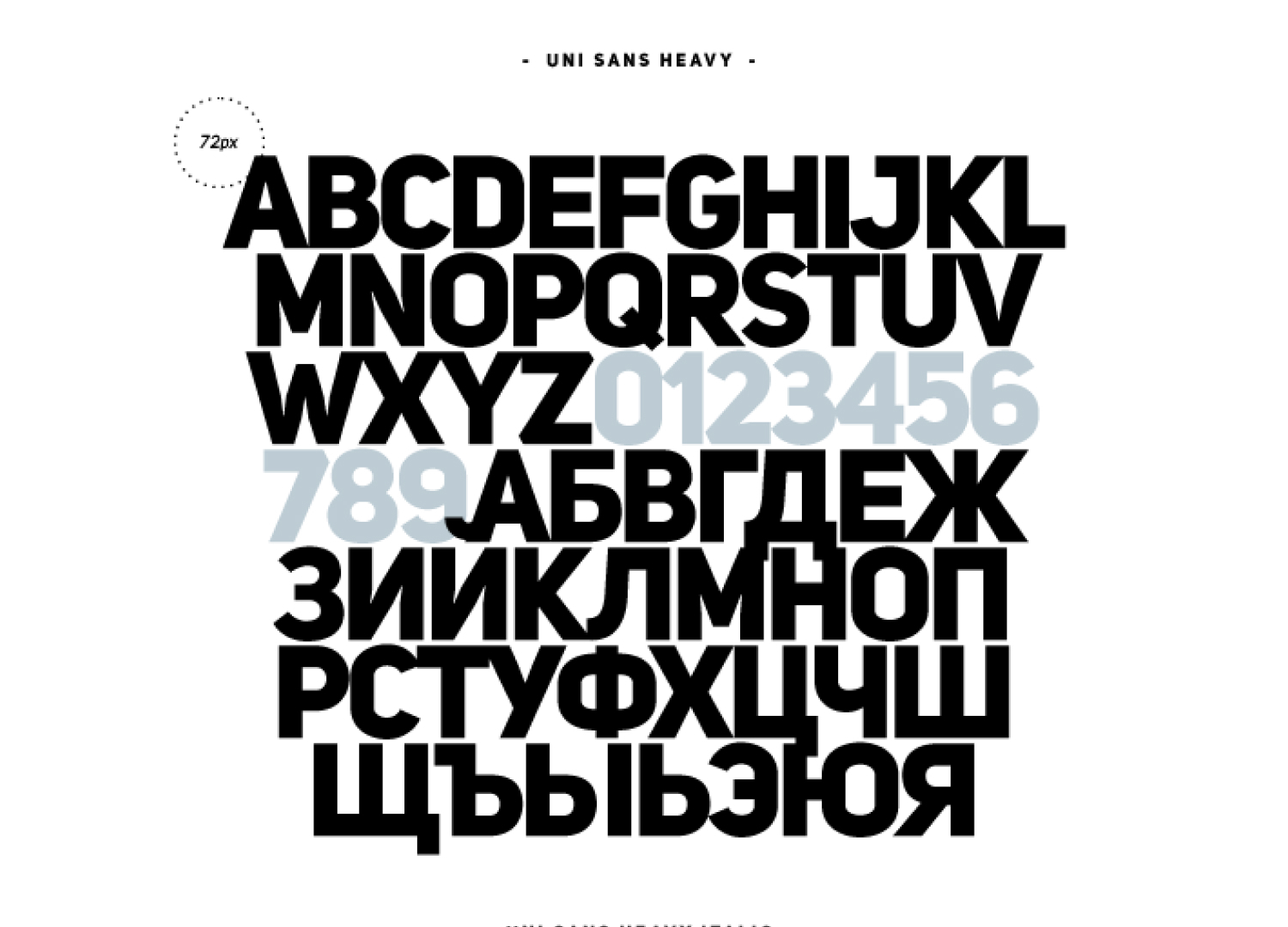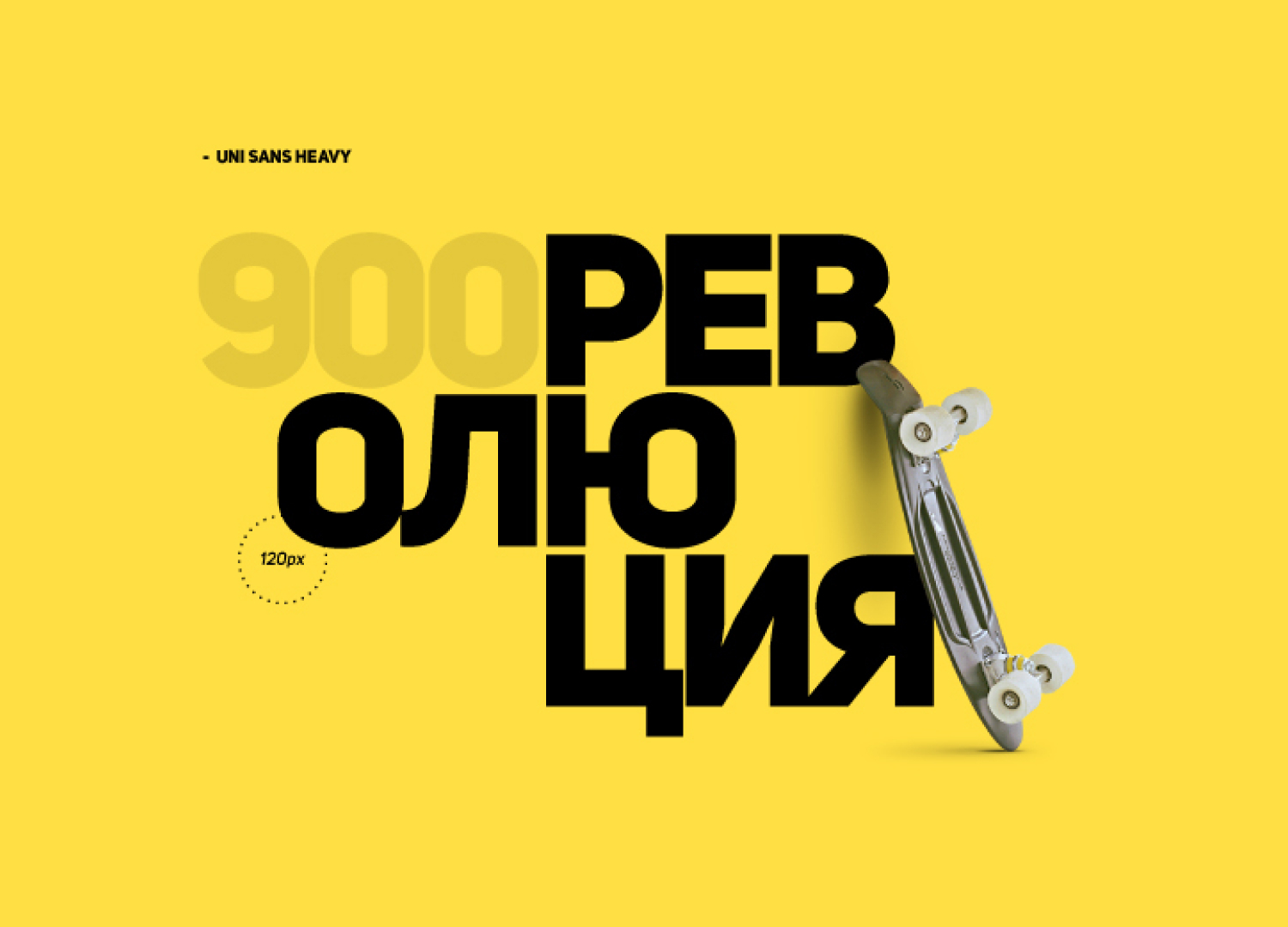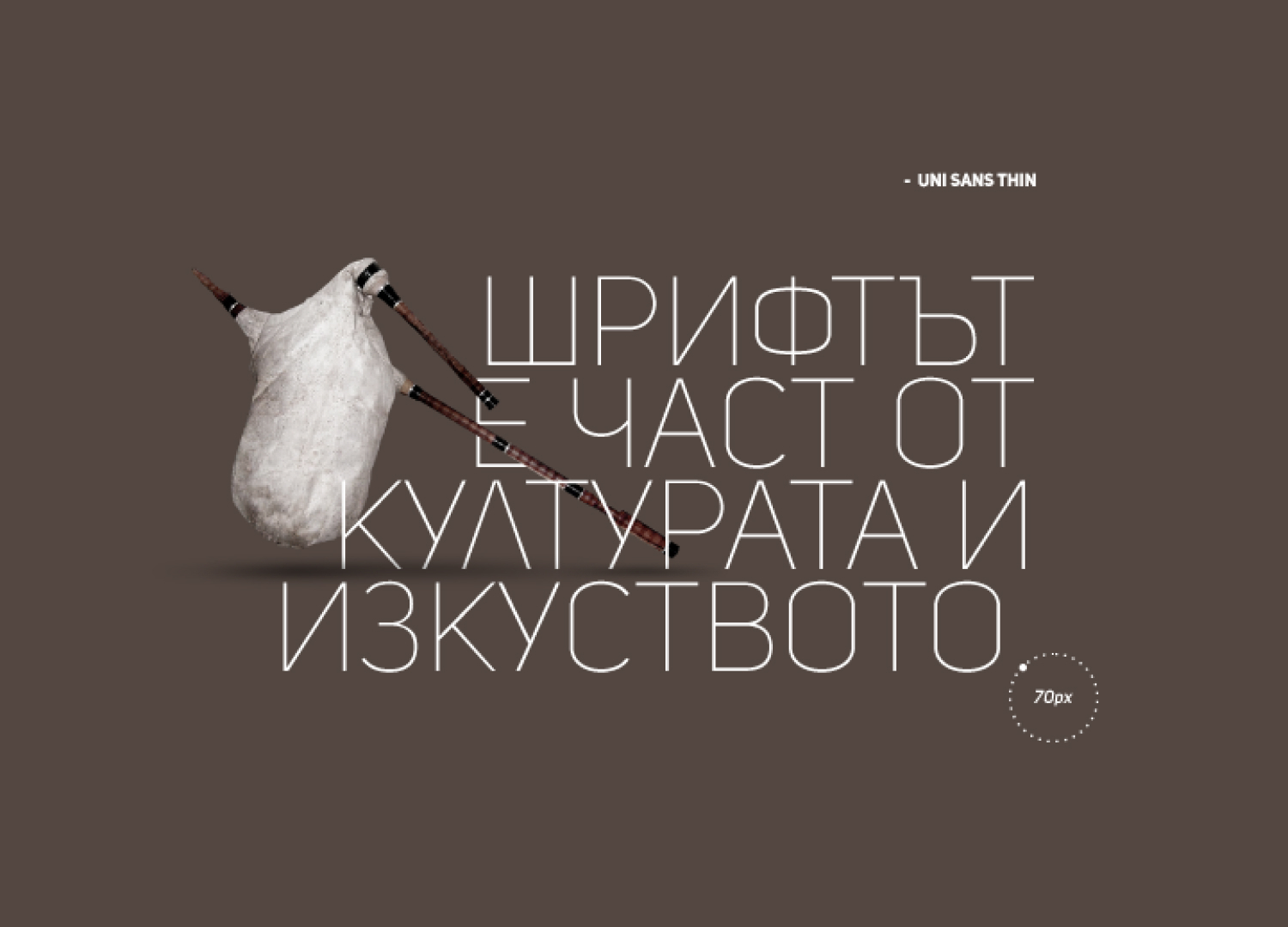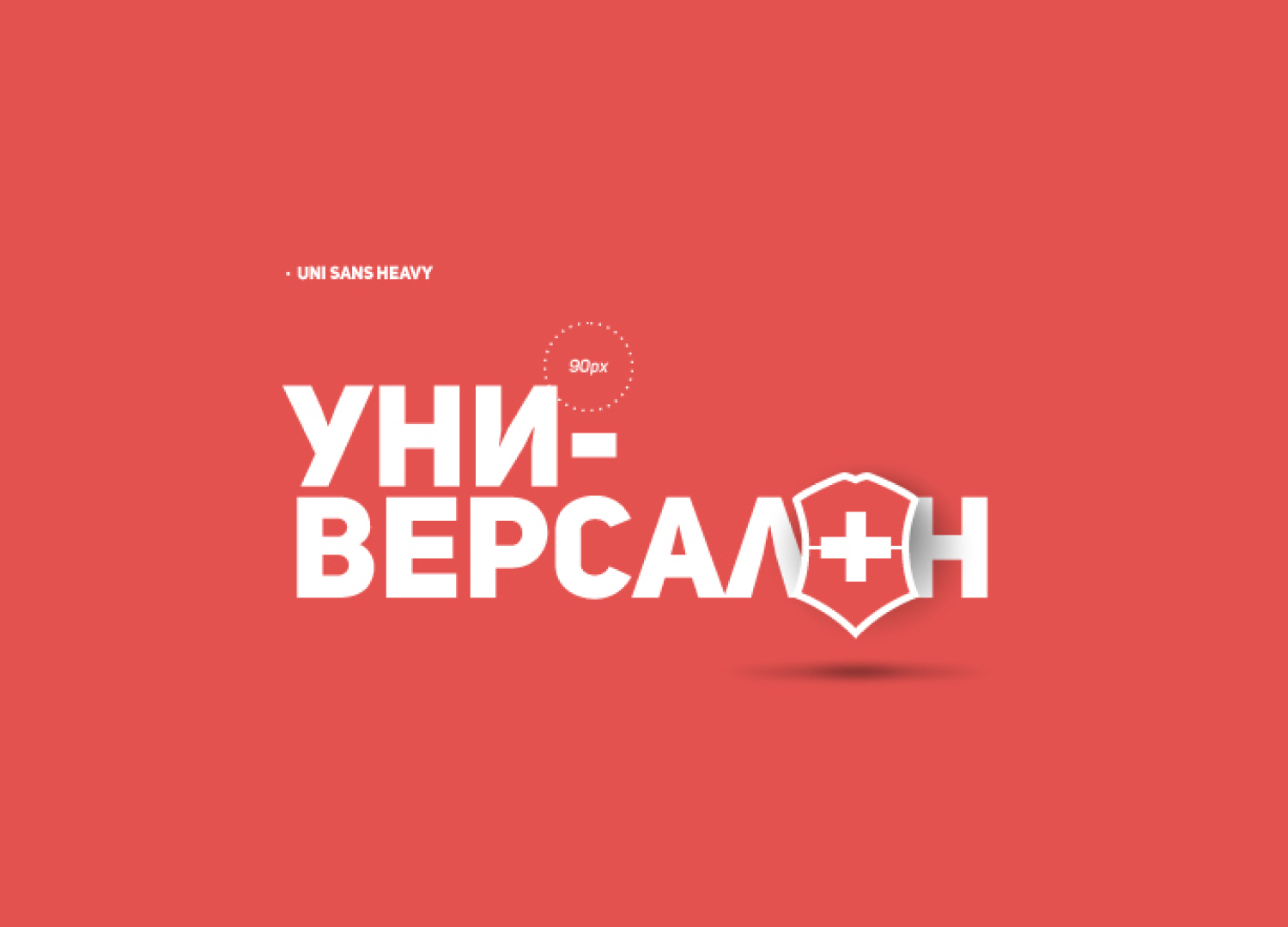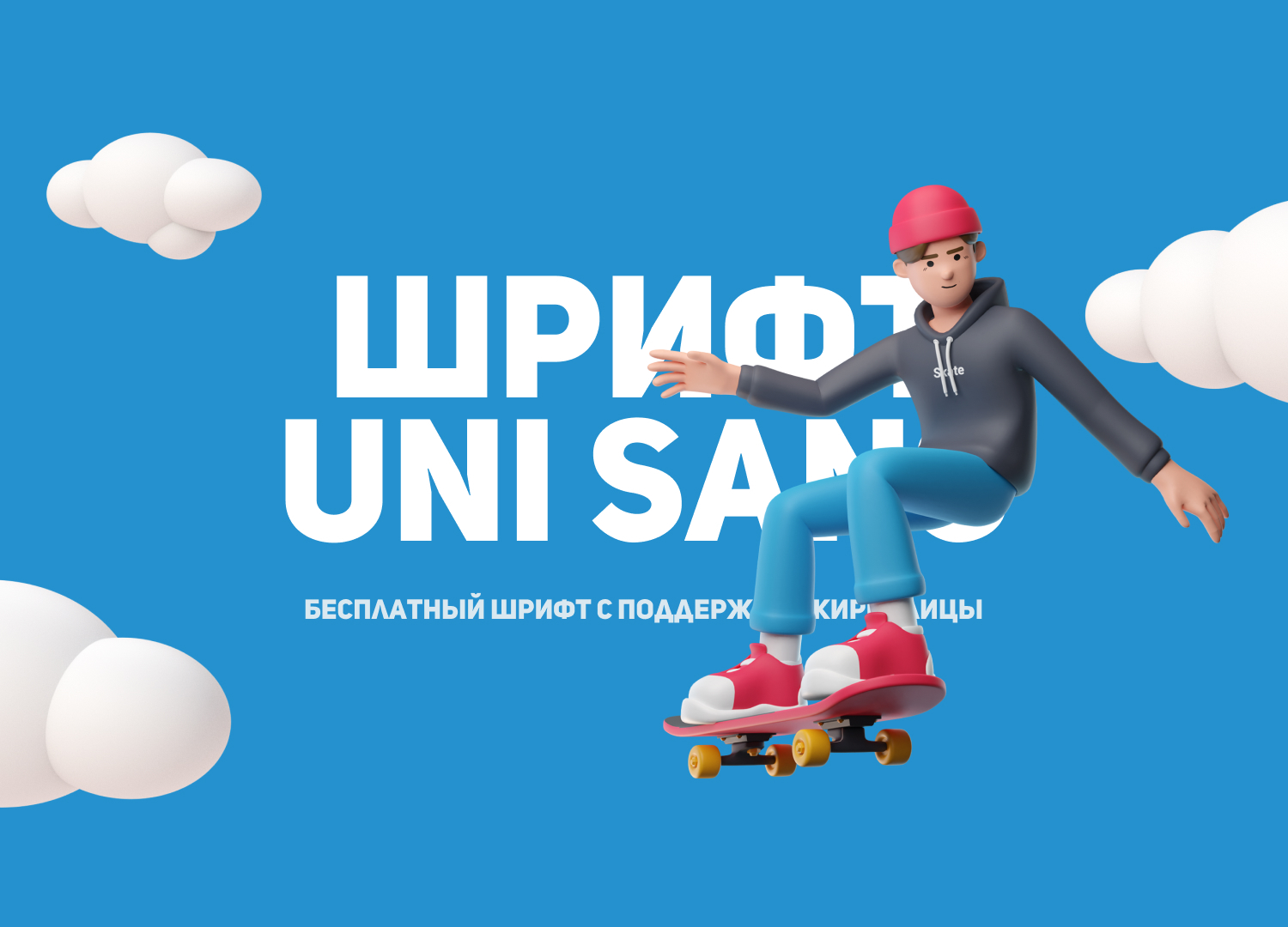
Бесплатный шрифт Uni Sans
Многим известный шрифт. Есть 4 начертаний. Уверенный и хорошо читаемый, особенно в крупных заголовках. Бесплатный для личного и коммерческого использования. Презентация сохранена от автора) Автор: Fontfabric Type Foundry